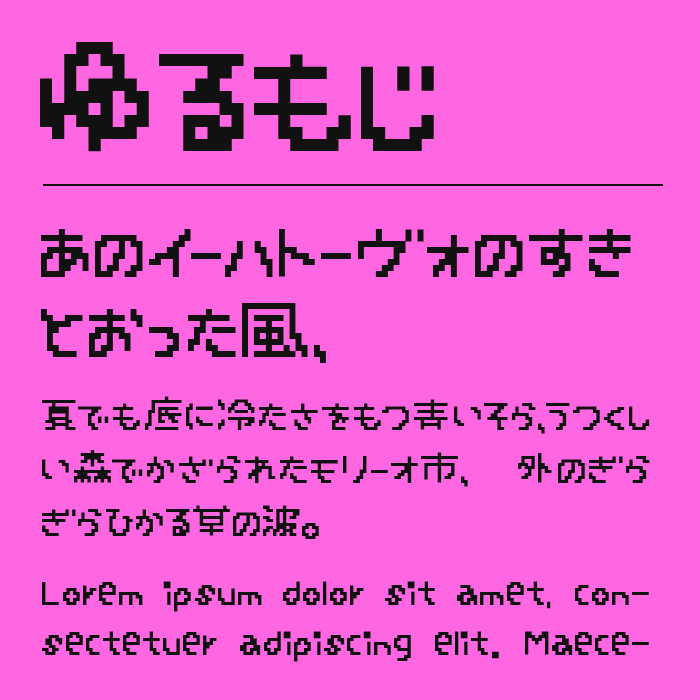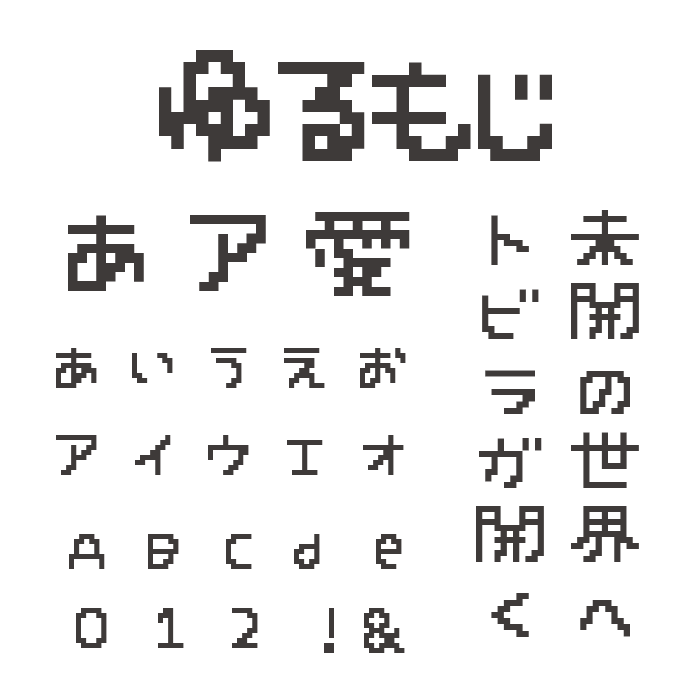
ゆるもじフォント
ゆるもじフォントは、ドットで構成されたシンプルな文字形に、どこか素朴な温かみを感じるピクセルフォントです。
レトロゲームを思わせる懐かしさを持ちながらも、角を少し丸めたような柔らかな印象があり、無機質になりすぎないのが魅力です。小さなサイズでも読みやすく、軽快で親しみやすい雰囲気のあるフォントです。
ゲーム風デザインやデジタル系のビジュアル、ポップなUIデザインなどと相性が良く、画面全体にかわいらしいレトロ感を加えられます。シンプルながらもクセになる表情があり、短いテキストでもしっかり印象に残ります。懐かしさとゆるさをバランス良く楽しめるフォントです。
ゆるもじフォント
収録文字は、漢字・ひらがな・カタカナ・アルファベット・数字・記号が収録。